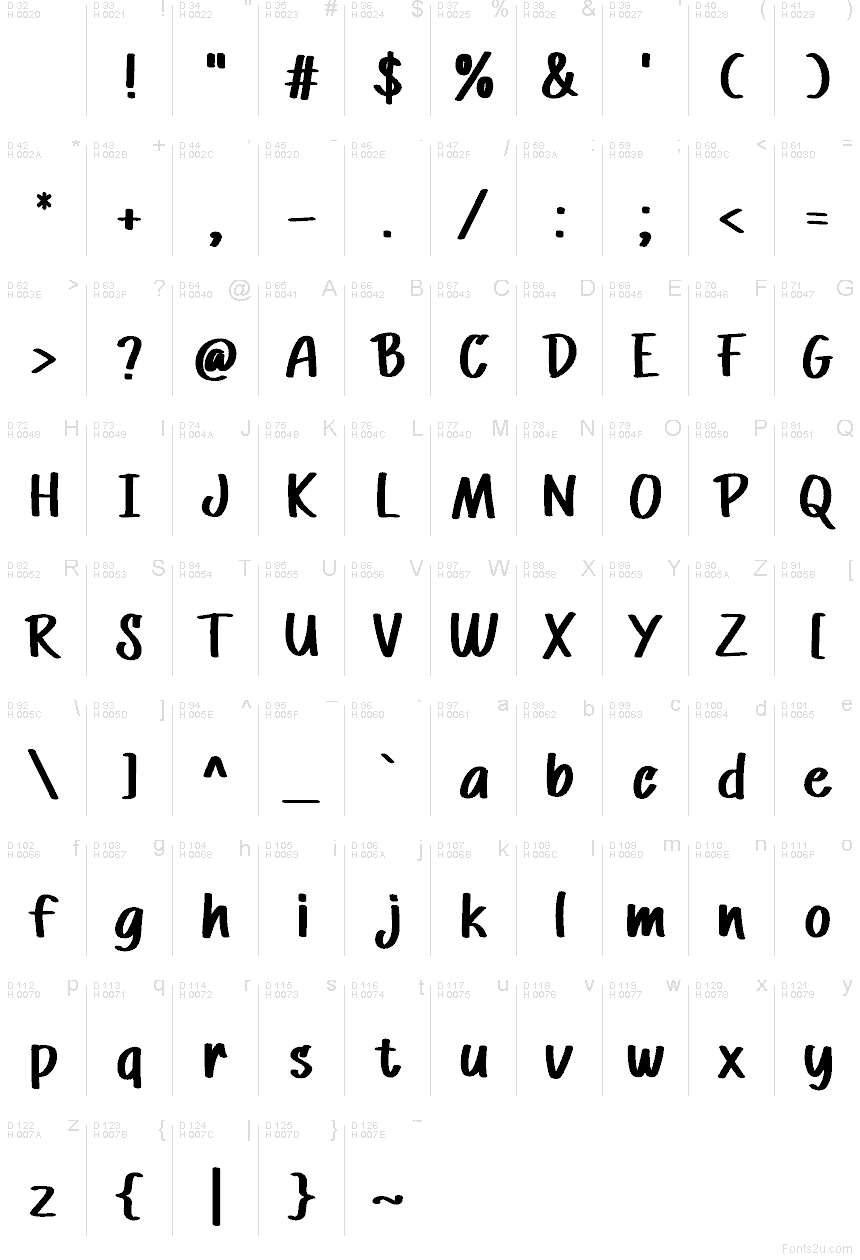
يعتبر ANIMAXI خطاً يدوياً مجانياً يتميز بضربات دائرية تشبه الفرشاة وإيقاع حر ومستقيم، مما يمنحه طابعاً شخصياً مرسوماً باليد. تظهر الحروف الكبيرة غير منتظمة قليلاً من حرف لآخر، مع منحنيات ناعمة ولمسة نهائية عفوية تمنع الخط من أن يبدو ميكانيكياً.
يعمل خط ANIMAXI بشكل ممتاز مع بطاقات الاقتباسات، وشعارات العلامات التجارية، وعناوين الملصقات، وتغليف المنتجات، ورسومات وسائل التواصل الاجتماعي التي تتطلب لمسة يدوية. يوفر هذا الخط المجاني ذلك من خلال شكل ضرباته غير الرسمي ومسافاته المريحة، مما يساعد النصوص القصيرة على الشعور بالعفوية والمباشرة دون أن تبدو متكلفة.